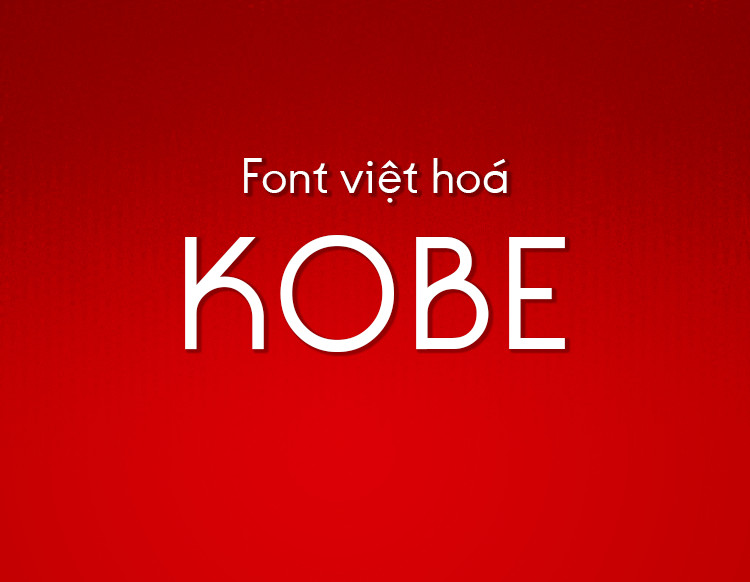
font việt hoá MJ Kobe ( Regular )
Thiết kế và Đặc điểm
MJ Kobe (Regular) có thiết kế gọn gàng, dễ đọc với các đường nét mềm mại, nhẹ nhàng. Sự cân đối giữa chiều cao và chiều rộng của các ký tự giúp cho font chữ này trở nên thân thiện và dễ dàng tiếp cận với người dùng. Các ký tự được thiết kế với độ dày đồng nhất, mang lại cảm giác ổn định và chắc chắn cho văn bản. Điều này rất quan trọng khi sử dụng trong các tài liệu chính thức hay quảng cáo, nơi mà tính chuyên nghiệp được đánh giá cao.
Tính Thẩm Mỹ
Khác với nhiều font chữ khác, MJ Kobe (Regular) mang đến một vẻ đẹp riêng biệt với các chi tiết tinh tế. Những đường cong mềm mại được sử dụng để tạo ra sự uyển chuyển, giúp cho văn bản trở nên sống động hơn. Đặc biệt, font chữ này còn thể hiện được nét văn hóa Việt Nam qua việc tích hợp các dấu sắc, huyền, hỏi, ngã một cách hoàn hảo, tạo nên sự hài hòa giữa các ký tự.
Ứng Dụng
MJ Kobe (Regular) có thể được sử dụng trong nhiều lĩnh vực khác nhau. Từ việc thiết kế logo, banner quảng cáo cho đến các tài liệu in ấn như brochure, tờ rơi hay sách báo. Với tính linh hoạt của mình, font chữ này phù hợp cho cả môi trường trực tuyến và ngoại tuyến. Người dùng có thể dễ dàng áp dụng MJ Kobe trong các dự án sáng tạo của mình mà không lo ngại về việc làm mất đi tính chuyên nghiệp.
Tương Thích
Kết Luận
MJ Kobe (Regular) không chỉ là một font chữ thông thường mà còn là một phần không thể thiếu trong bộ sưu tập của những người yêu thích thiết kế. Với sự kết hợp hoàn hảo giữa tính thẩm mỹ và tính ứng dụng, font chữ này mang lại cho người dùng cảm giác thoải mái khi làm việc. Nếu bạn đang tìm kiếm một font chữ độc đáo và tiện dụng cho các dự án của mình, MJ Kobe (Regular) chắc chắn là một lựa chọn tuyệt vời. Hãy thử nghiệm và cảm nhận sự khác biệt mà font chữ này mang lại cho các sản phẩm thiết kế của bạn!